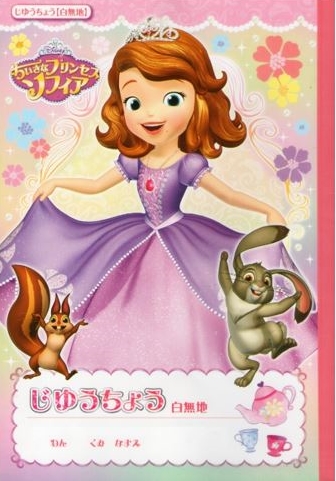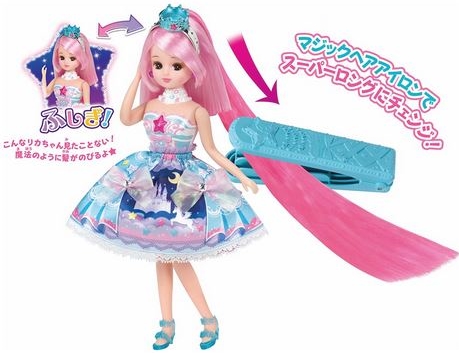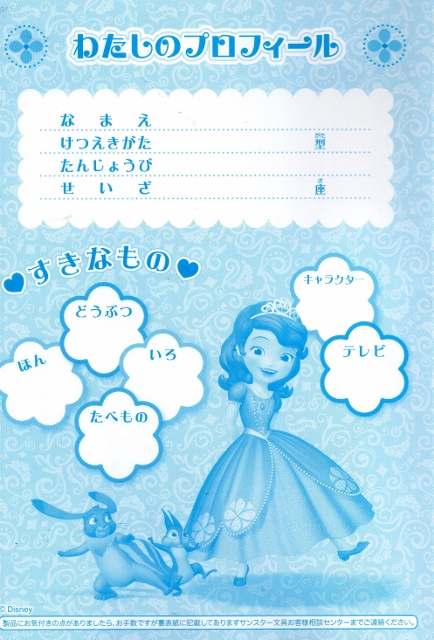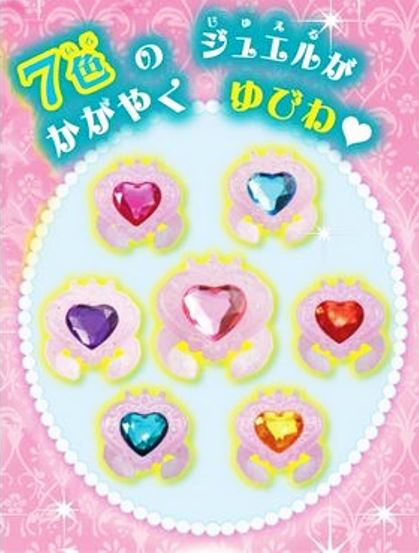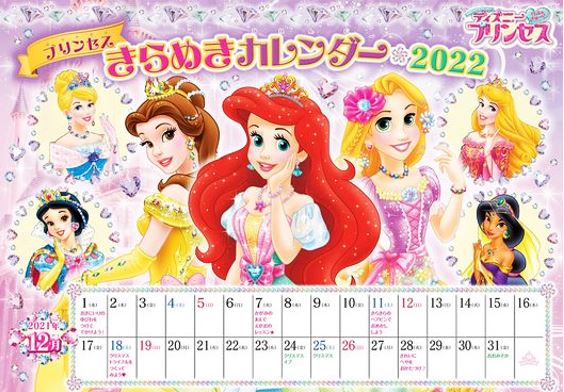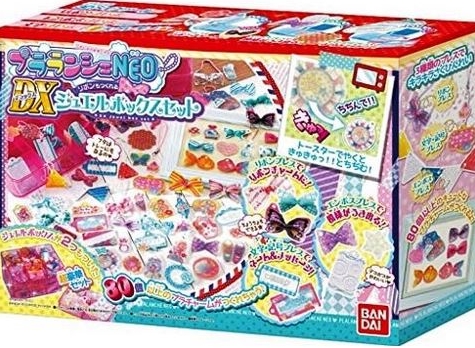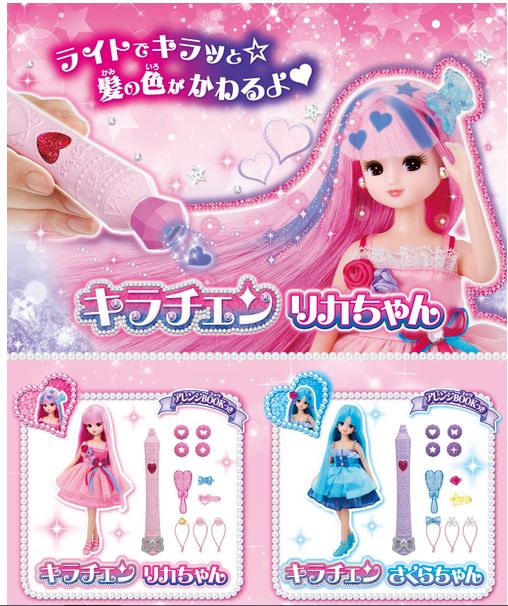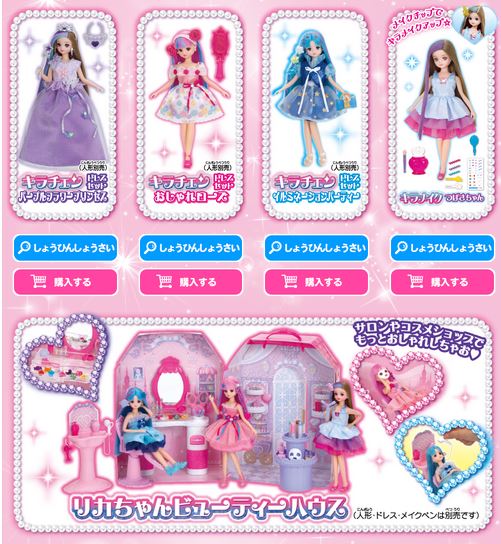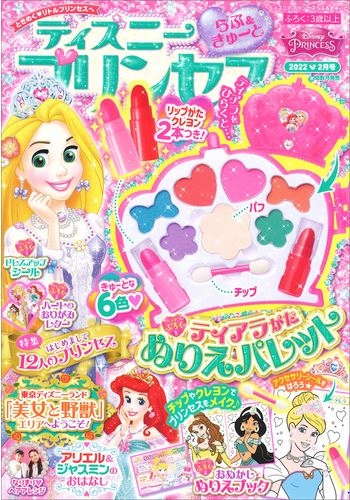
パンのパッケージ。
カニクリームコロッケ
期間限定
弁当店のノボリ
Airペイ(エアペイ)のCM。
最新のCMでも「使われているようです。
マジックロングヘアリカちゃん
発売 タカラトミー
家電量販店玩具売り場で見つけました。
筆記具の広告。
もうひとつ。
トロピカル~ジュ プリキュア
ミニハードルージュロッド
発売 ハピネット
ショッピングセンターで。
ゆめいろリカちゃん
カラフルチェンジデラックス
発売 タカラトミー
ショッピングセンター玩具売場で。
トロピカル~ジュ プリキュア
きせかえシールあそびえほん
発売 講談社
ショッピングセンター書籍売り場で。
カニクリームコロッケ弁当
発売 Hotto motto
2月2日発売 期間限定
店頭に掲げられている垂れ幕です。
※角が丸く加工されていますが、特徴はそのままなので
「えれがんと」だと思います。違っていれば削除します。
びっくらたまご ディズニープリンセス
アクセサリーマスコット
発売 バンダイ
ショッピングセンター玩具売場で。